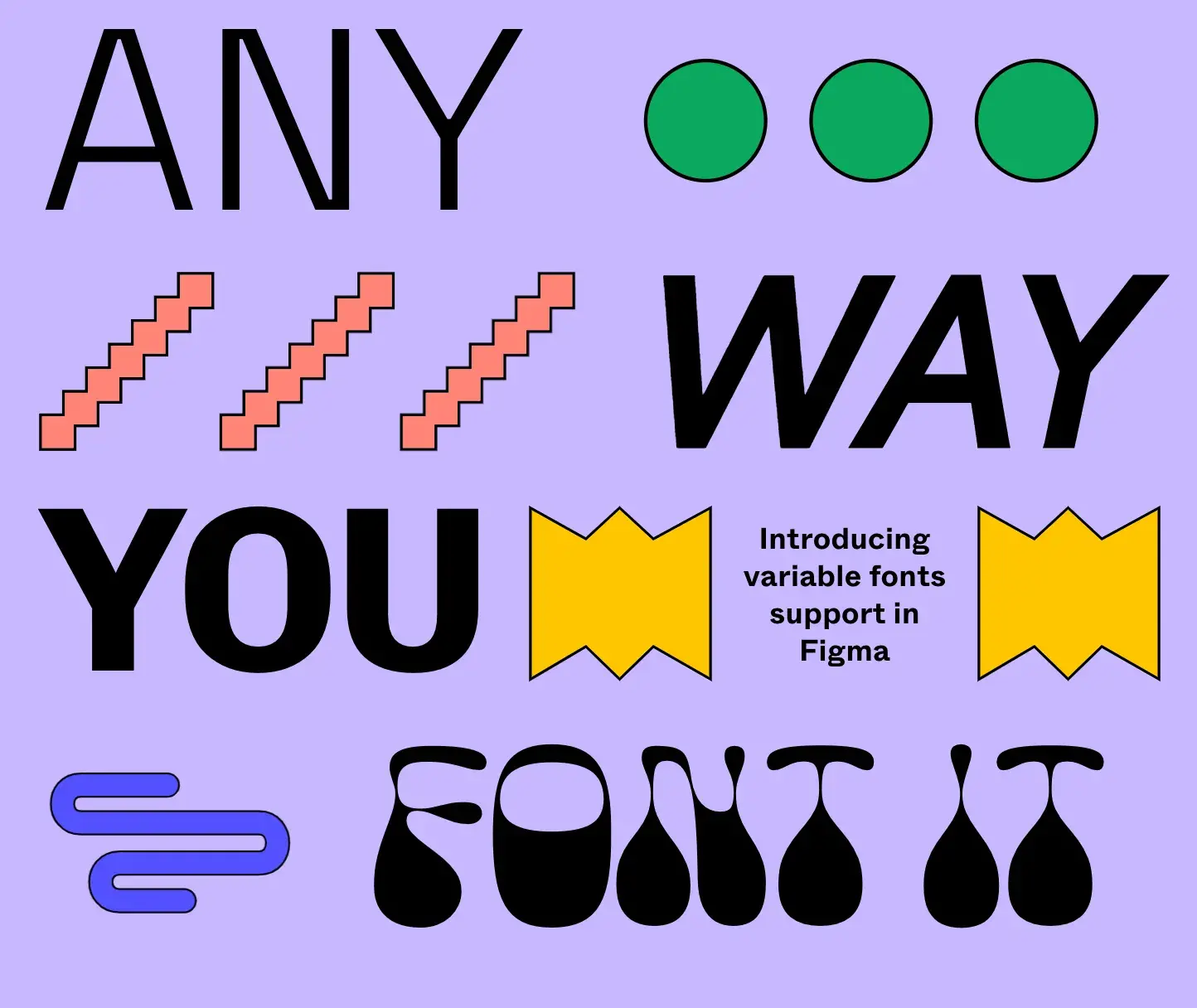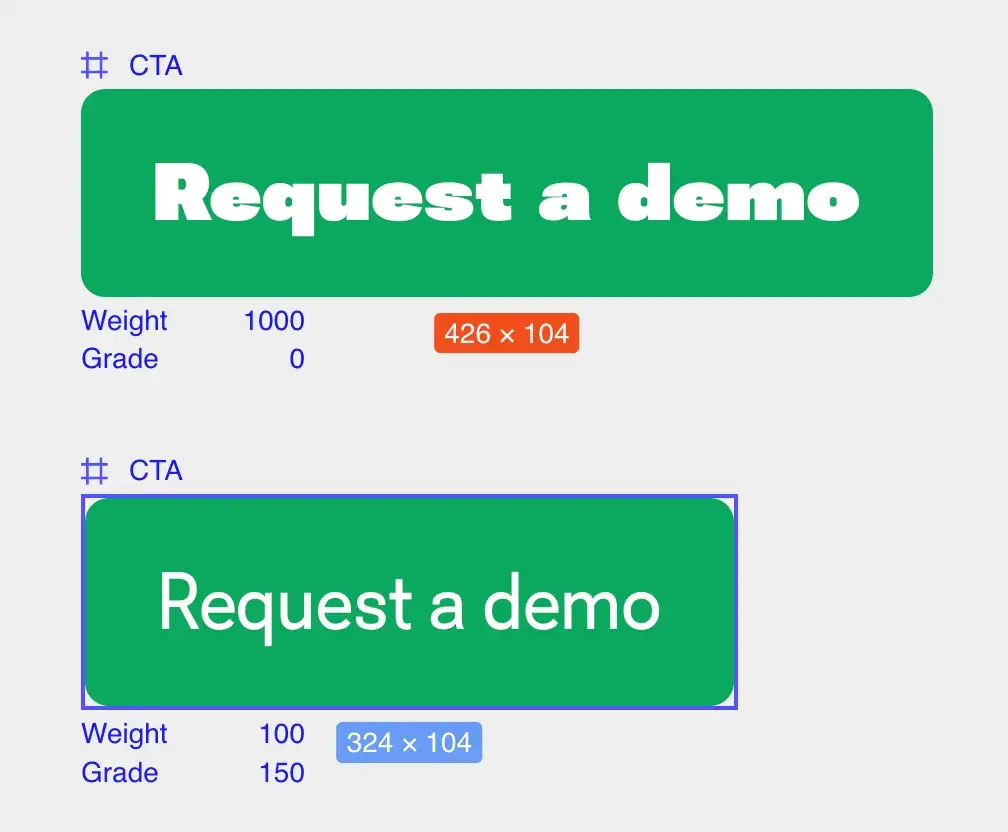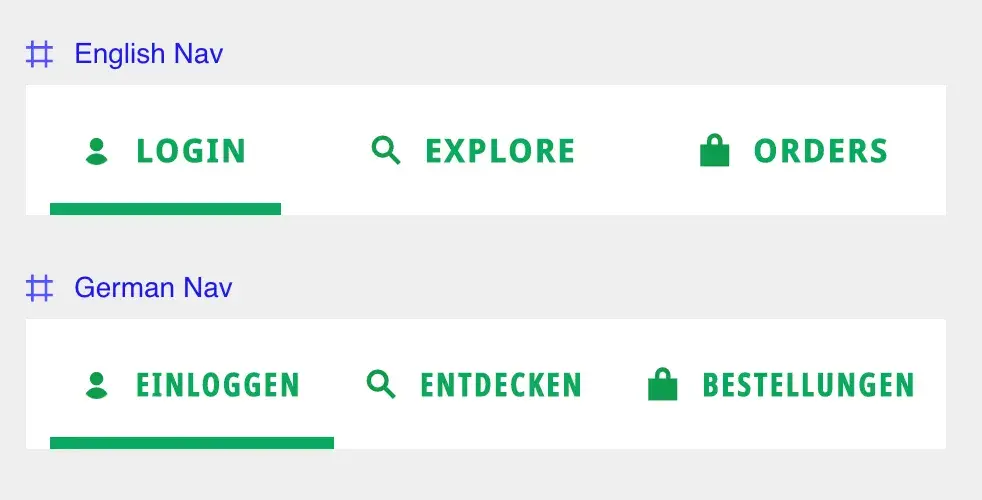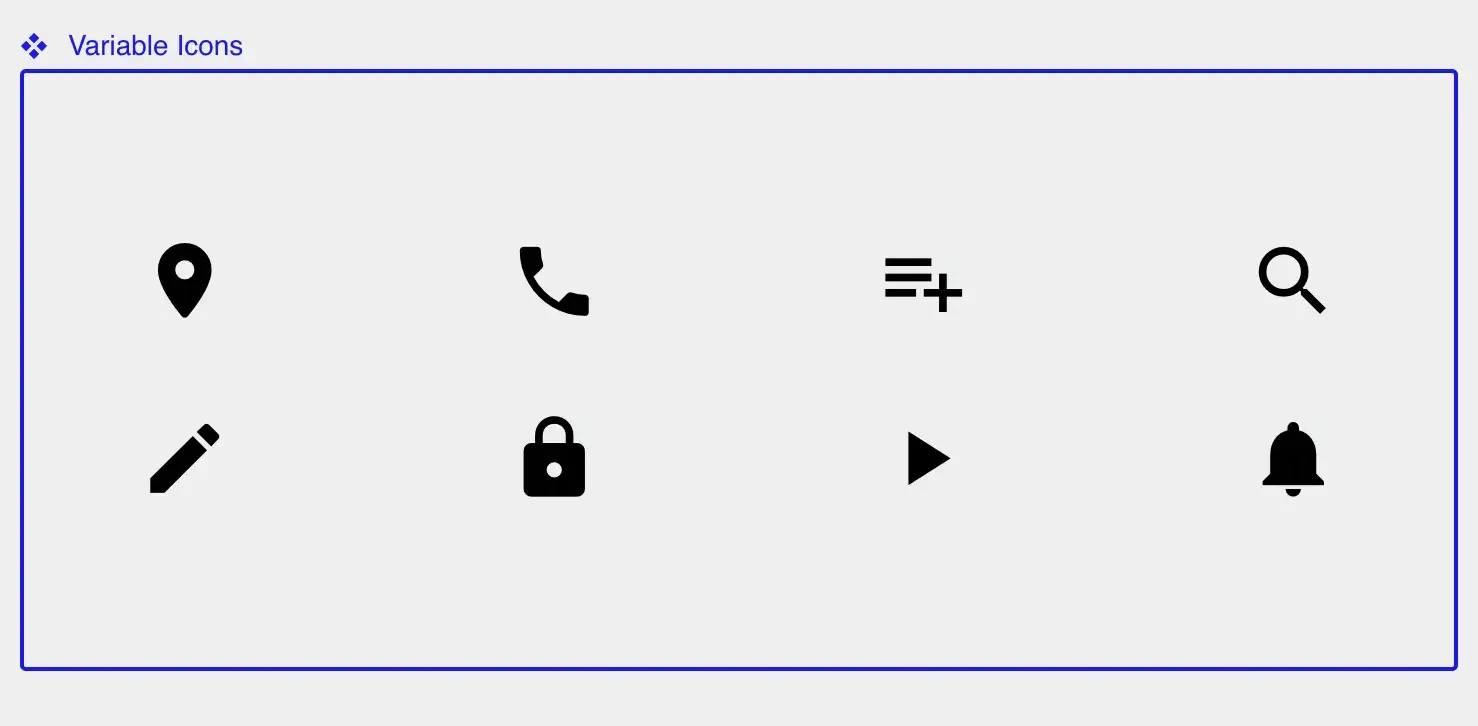
Шрифты в Figma: как настроить и использовать
Рассказываем, как настроить интерлиньяж, разрядку, абзацные отступы и установить дополнительные шрифты.
Figma — очень удобна для веб-дизайнера благодаря встроенной интеграции с библиотекой Google Fonts. Но помимо этого она даёт пользователю много настроек шрифта, которые помогают очень тонко отрегулировать все текстовые блоки на макете. О том, где найти все эти настройки, — читайте в нашей инструкции.
9 мая 2022 года разработчики Figma выпустили обновление. В графическом редакторе изменился интерфейс и появились новые функции. Эта инструкция всё ещё может помочь вам освоить работу со шрифтами, но если вы только начали пользоваться Figma, советуем прочитать обзор последних обновлений.
Выбор шрифтов и базовые настройки
Шрифты отображаются на панели инструментов справа в блоке Text. В нём есть несколько полей, которые помогут вам с настройками типографики:
• Сам шрифт — отображается как его полное название. По умолчанию Figma предлагает пользователю использовать Roboto, но вы можете выбрать любой из доступных.
• Начертание — находится под названием шрифта. Количество начертаний и их названия зависят от разработчика шрифта, но обычно это light, regular и bold.
• Кегль, или размер шрифта, — находится напротив начертания.
• Разрядка || — расстояние между буквами.
• Интерлиньяж — расстояние между строками.
• Абзацный отступ .
• Выравнивание.
Горизонтальное — по центру , по левому или правому флагу . Вертикальное — вверх , вниз или по центру .
Если нажать на иконку , вы откроете дополнительные настройки шрифта. В них вы можете добавить зачёркивание, линию под текстом, капитель и настроить список.
Управление отсутствующими шрифтами
Если коллега отправил вам файл без необходимых шрифтов, Figma предупредит об этом вот таким уведомлением:
Чтобы редактировать все текстовые объекты в проекте, нужно установить или обновить недостающие шрифты на вашем устройстве. Вы также можете выбрать другой подходящий шрифт из уже имеющихся, но при этом помните, что он изменится и для вашего коллеги.
Чтобы изменить шрифт, в уведомлении кликните на поле с жёлтым квадратом и выберите замену. При необходимости можно изменить и начертание:
Поддержка вариативных шрифтов в Figma
Вариативные шрифты появились еще в 2016 году и с тех пор завоевали большую популярность среди дизайнеров и разработчиков.
Вариативные шрифты: основы
Вариативный шрифт — это файл, который включает целый диапазон стилей, предоставляя дизайнерам больше контроля и возможностей для творческих экспериментов.
В чем разница между статичными и вариативными шрифтами?
Статичный шрифт представляет собой часть “семейства шрифтов”. Он привязан к одному определенному стилю и обычно имеет фиксированные параметры, такие как «полужирное» или «курсивное» начертание. Вариативные шрифты включают одну или несколько осей, что позволяет предложить гораздо более широкий выбор стилей.
Что такое ось?
Ось — это выражение одного изменяемого свойства шрифта. Например, «ширина» (width) определяет, насколько узким или широким может быть символ. “Вес» (weight) — насколько легким или жирным он может быть.
Какие виды осей существуют?
Большинство осей содержат непрерывный диапазон значений, однако некоторые из них являются бинарными. Бинарная ось — это переключатель, то есть существует только два варианта: выключить или включить (в нашем примере — курсив или не курсив). Ось с диапазоном значений дает больше возможностей для увеличения или уменьшения свойства, например, наклона.
Как вариативные шрифты меняют процесс разработки
7. Anicons от Wenting Zhang и Hua Shu. Первый в мире цветной анимированный иконочный шрифт, основанный на иконках Material Design. Anicons — это эксперимент, сочетающий в себе две передовые шрифтовые технологии: вариативные и цветные шрифты.
8. WT Zaft² от WiseType. Zaft² — это 3 вариативных шрифта, каждый из которых включает уникальную ось управления и имеет свою собственную форму.